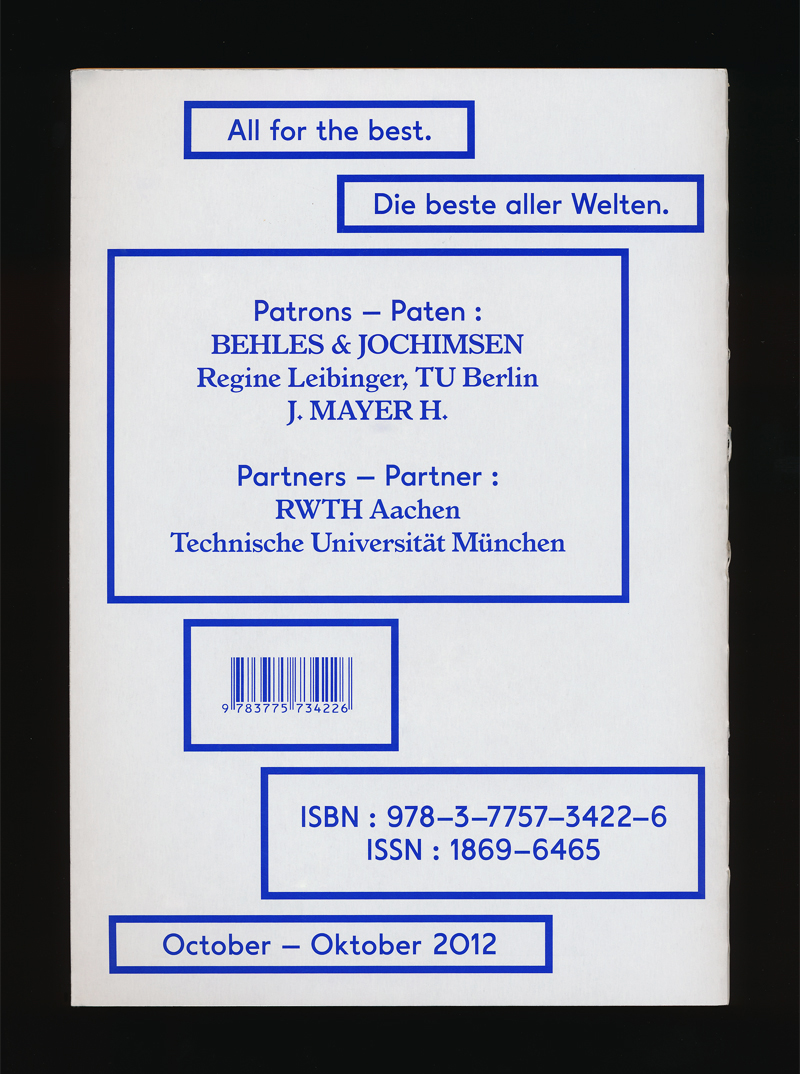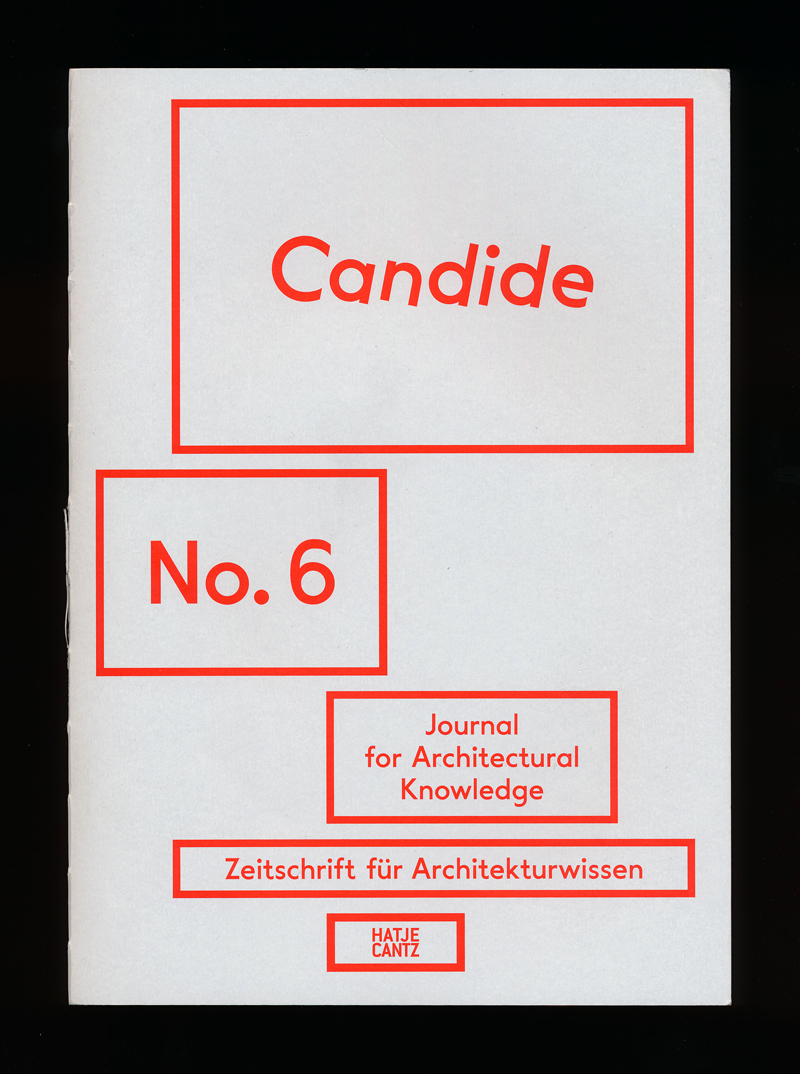
Schrift gesucht: ähnlich wie Futura/Futurainterpretation
bin letztens auf eine Schrift gestoßen, die mich an die Futura erinnert, dennoch z.b. beim ‘g‘ von dieser abweicht. Außerdem, so kommt es mir vor, fällt diese im höhen-breiten-verhältnis mehr 'hoch' aus. ;)
Kennt jmd. vll diese Schrift?
Ich dachte erst an die Metric von Kris Sowersby, aber da stimmen beispielsweise das t und die Ziffern nicht. Nur dass die anderen gar nicht erst dort schauen müssen …
Die Brown kommt dem schon ziemlich nahe; ist auch eine schöne Schrift!
Ich hätte ja fast auf die Super Grotesk getippt, aber die hat statt Punkten Quadrate...
Sicher? Das würde ich bezweifeln.
Ich nicht. ;)
Nein, ich denke, dass für die Zeitschrift eine leicht modifizierte (frühere?) Version der Value Sans zum Einsatz kommt. Das macht auch insofern Sinn, als dass der Gestalter der Publikation offensichtlich auch der Schriftgestalter ist.
Die Value Sans ist ziemlich weit davon entfernt. Ich sehe da noch nicht mal eine "leicht modifizierte Version", dafür sind die Buchstaben einfach zu unterschiedlich.
Schwarz = Value Sans
Rot = gesuchtes Original
Die Value Sans ist ziemlich weit davon entfernt.
Wie gesagt, sollte es sich bei der gesuchten Schrift um eine exklusive handeln, ist man mit der Value Sans noch am besten bedient. Alle anderen genannten Schriften sind wesentlich weiter von der gesuchten entfernt.